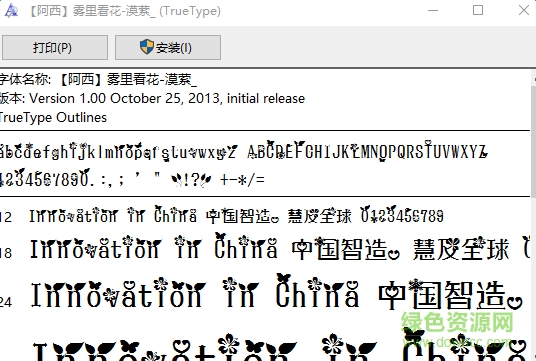
霧里看花
霧里看花字體是一款很有意境的電腦個(gè)性字體,這款字體寫(xiě)出來(lái)的效果是很不錯(cuò)的,還有很多小花兒、樹(shù)葉的裝飾,這也是這款字體的魅力之處,喜歡這款字體的朋友可以來(lái)綠色資源網(wǎng)下載。
霧里看花字體是一款很不錯(cuò)的字體,寫(xiě)出來(lái)的字效果很不錯(cuò),適合用于藝術(shù)設(shè)計(jì)、廣告設(shè)計(jì)等方面,歡迎有需要的朋友來(lái)綠色資源網(wǎng)下載。